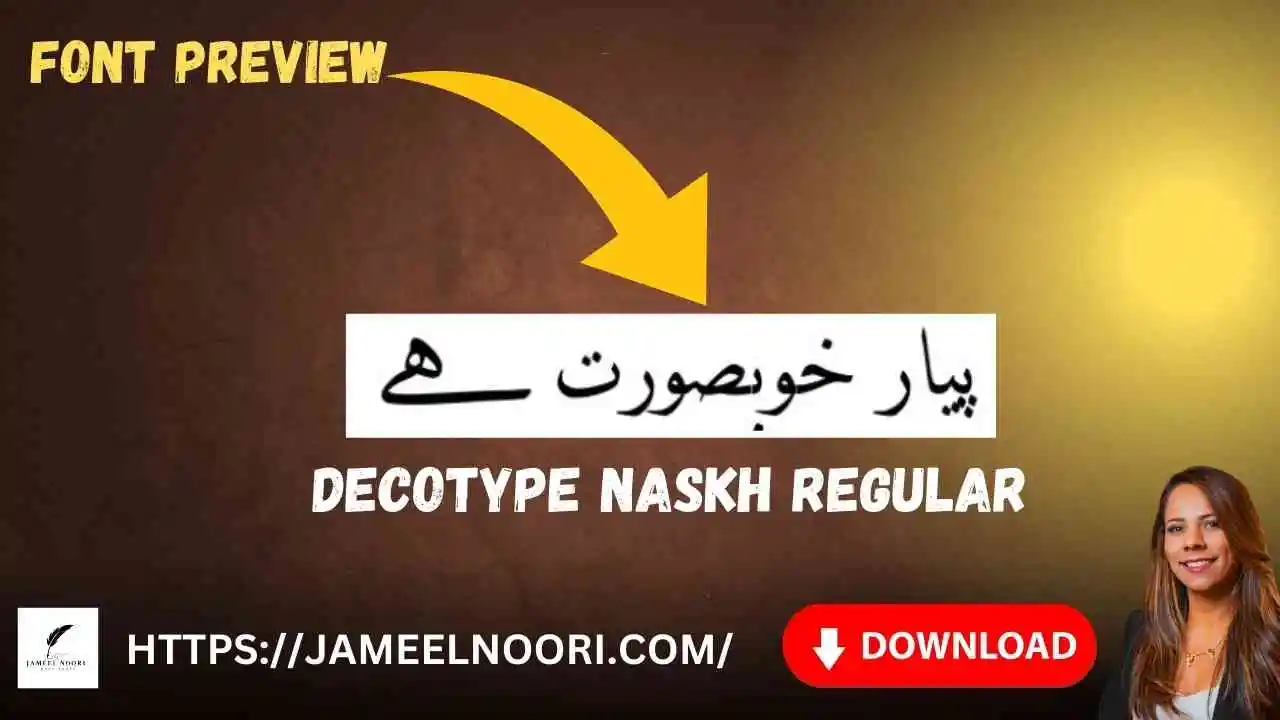
Agar aap Urdu typing ke liye ek khubsurat aur readable font dhoond rahe hain, toh Download Urdu font DecoType Naskh Regular karna aap ke liye behtareen choice hai. Yeh font na sirf visually appealing hai balkay readability bhi kaafi high hai, jo ise professional Urdu document writing ke liye perfect banata hai.
Overview to DecoType Naskh Regular Font
Key Features of This Font:
- Regular aur clean style
- Easy to read on screen and paper
- Stylish yet simple design
- Urdu books aur content writing ke liye suitable
What type of font is DecoType Naskh Regular?
It is a Regular TrueType Urdu font designed for clear and elegant Urdu script.